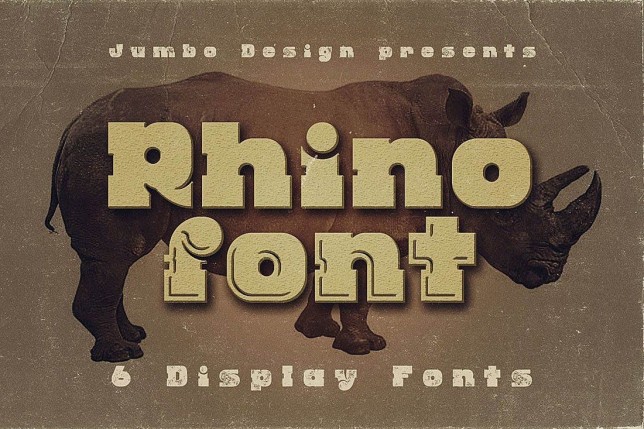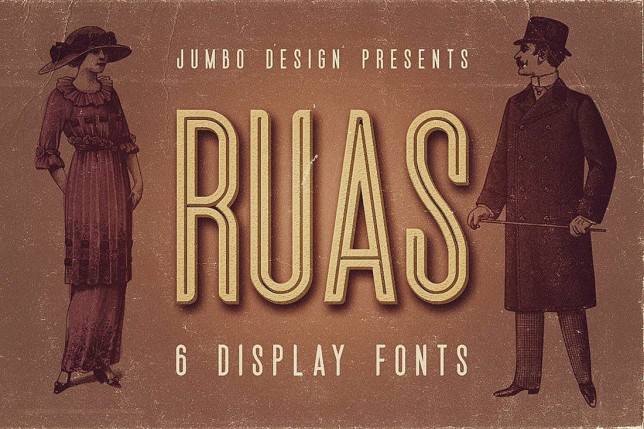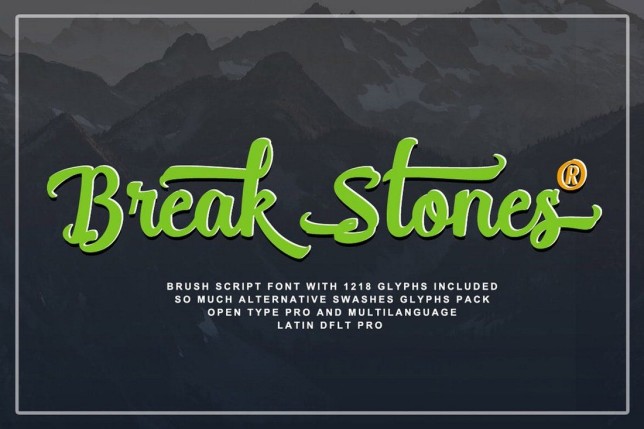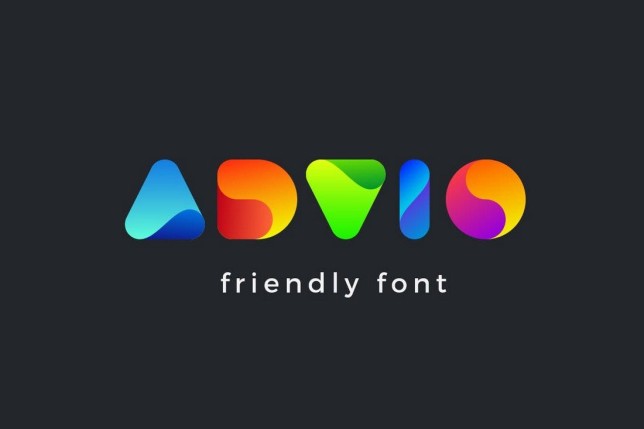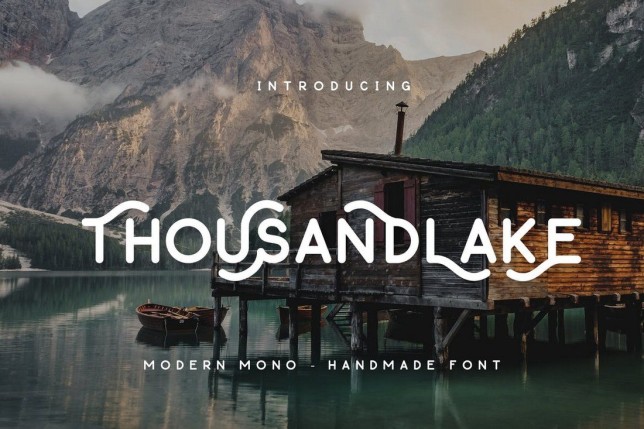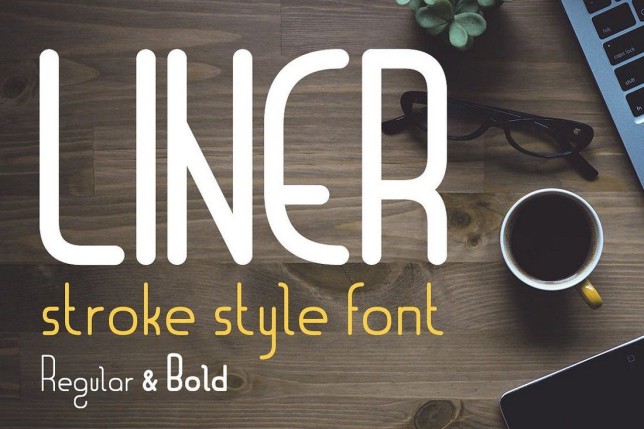
Việc thiết kế nên một logo hoàn hảo thường đòi hỏi nhiều thời gian và công sức. Bạn phải đưa ra một phác thảo thiết kế, chọn những màu sắc phù hợp, và tìm một kiểu chữ hoàn hảo để phù hợp với thương hiệu. Nhưng đừng lo, chúng tôi viết bài viết này chính là để quá trình này trở nên dễ dàng hơn cho bạn.
Không cần thiết phải dành nhiều giờ để lướt web để tìm ra một kiểu chữ tuyệt vời cho thiết kế logo của bạn, chúng tôi đã chọn ra ở đây những font chữ tốt nhất cho bạn. Hãy xem qua bộ sưu tập những kiểu chữ logo bỏ túi này của chúng tôi và chọn ra kiểu chữ phù hợp nhất cho dự án thiết kế của bạn!
Nixmat – Font chữ nhận dạng thương hiệu
Nixmat là một font chữ mang tới một thiết kế hoàn toàn khác biệt khiến nó trở nên hoàn hảo khi tạo ra bộ nhận diện thương hiệu cho doanh nghiệp của bạn. Font chữ này có thể sử dụng để thiết kế logo, hồ sơ xin việc, danh thiếp và nhiều đối tượng hơn nữa.
Bowlist – Font chữ cho logo
Bowlist là một kiểu chữ sáng tạo và đậm nét cho phép bạn có được những thiết kế logo hiện đại và phá cách. Font chữ này có thể được sử dụng cho thiết kế poster, tiêu đề website hoặc thiết kế áo phông. Nó đi kèm với bộ 376 glyph và 161 kí tự đặc biệt khác.
Oxigen – Font chữ logo tối giản
Oxigen là một font chữ logo độc đáo theo phong cách tối giản phù hợp nhất cho thiết kế logo của những thương hiệu thời trang hoặc những mặt hàng cao cấp. Nó mang lại một thiết kế đầy phong cách cũng có thể giúp bạn thiết kế nhận diện thương hiệu có thể nổi bật trước đám đông.
Raisa Script – Font chữ cho logo
Font chữ tinh tế này đi kèm với đường nét uyển chuyển một cách tự nhiên khiến nó thực sự đại diện cho sự tao nhã và thanh lịch. Kiểu chữ này lý tưởng cho việc thiết kế logo cho nhiều ngành nghề kinh doanh khác nhau cũng như tạo nên những danh thiếp, thiết kế áo phong và thiệp mời đám cưới.
Magehand – Font chữ cho logo
Magehand là một font chữ logo có một thiết kế khá sáng tạo. Nó cung cấp cả tùy chọn chữ in hoa và chữ thường cũng như nhiều kí tự thay thế đa dạng cho những ngôn ngữ khác nhau.
CAOS – Font chữ cho logo
Caos không chỉ có một thiết kế dạng monogram độc đáo thu hút sự chú ý mà còn có thể biến thiết kế của bạn thành một tác phẩm nghệ thuật. Kiểu chữ này là hoàn hảo cho việc thiết kế logo cho những hãng chuyên về sáng tạo.
Metropolia – Futuristic Font
Metropolia là một font theo phong cách Futuristic mang trong mình một thiết kế đầy sáng tạo và độc đáo. Nó phù hợp nhất khi sử dụng để thiết kế logo, danh thiếp, đầu đề trang web cho những dự án khởi nghiệp công nghệ cao và những hãng thiết kế web.
Duffish – Font chữ cho logo
Duffish là một font chữ sáng tạo cho thiết kế logo với những đường nét đậm nét và cá tính. Kiểu chữ này cung cấp đầy đủ tùy chọn với đa dạng các kí tự thay thế với những cách bố trí độc đáo giúp bạn thiết kế ra được những logo, đầu đề website hấp dẫn và nhiều hơn thế nữa.
Ornacle – Futuristic Font
Ornacle là một font chữ logo khác với phong cách Futuristic. Nó mang trong mình những đường nét sáng tạo khiến kiểu chữ này trông giống một tác phẩm nghệ thuật chạm khắc cổ xưa. Bạn có thể sử dụng nó để tạo nên những logo, poster, tiêu đề website và nhiều hơn thế nữa.
Lineat III – Font chữ sáng tạo
Họ font Lineat có đặc trưng là sự hòa trộn giữa những nét hiện đại và tương tai. Thiết kế trôi chảy dạng đường một cách sáng tạo của nó khiến kiểu chữ này lý tưởng cho việc thiết kế những logo cho những doanh nghiệp hay startup hiện đại, những nhãn hàng thời trang và thậm chí là cho cả những blogger.
RADON Monogram – Font chữ cho logo
Radon là một kiểu chữ dạng monogram với thiết kế sáng tạo mang đến một vẻ ngoài độ nhất, điều này khiến nó lý tưởng cho việc xây dựng những logo và tiêu đề trong website, danh thiếp và những thiết kế bản in. Font chữ này cũng tích hợp cả bộ chữ thường, đậm và bộ kí tự trang trí.
RibOne – Font chữ cho logo
Font chữ đầy phong cách và độc đáo này có một thiết kế đẹp mắt – khiến nó trở nên tuyệt vời cho việc thiết kế logo cho những hãng thiết kế hoặc thậm chí là tên của một sản phẩm. Nó cũng bao gồm một phiên bản web và một phiên bản chuyển sắc EPS.
Adrift Font
Nếu bạn đang thực hiện một thiết kế logo cho một thương hiệu theo chủ nghĩa tối giản hoặc thiết kế nhãn mác cho một sản phẩm, Adrift sẽ là sự lựa chọn đáng cân nhắc. Nó có 4 tùy chọn phong cách khác nhau: viết thường, trung bình, đậm và làm nhám. Font chữ dưới dạng viết tay này chắc chắn sẽ bổ sung nhiều giá trị cho những thiết kế của bạn.
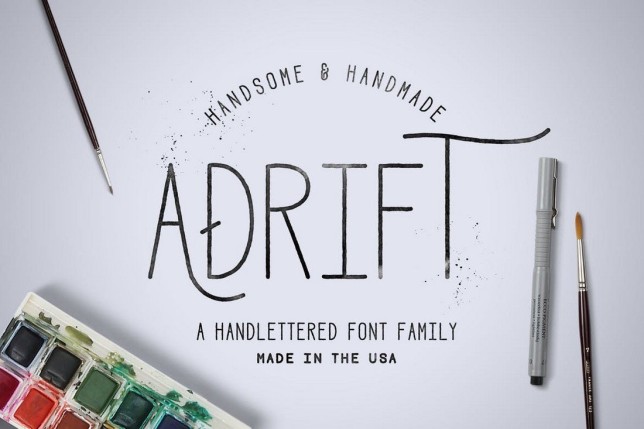
Những font chữ hoài cổ hiện đại
Những thiết kế hoài cổ hiện đại quả thực là một cơn sốt trong những năm gần đây. Font chữ này được thiết kế để giúp bạn xây dựng một logo cho thương hiệu theo sát xu hướng này. Kiểu chữ có sẵn ở 3 phong cách với những đường nét mềm mại, những đường nét tròn và một phong cách còn lại với phong cách thiết kế hỗn hợp.
Casses Font
Casses là một kiểu chữ hoàn hảo để xây dựng một logo hoặc nhãn mác sản phẩm cho quần áo hay những thương hiệu liên quan tới thời trang. Kiểu chữ này mang lại một thiết kế thủ công một cách tinh tế chắc chắn sẽ thu hút nhiều sự chú ý hơn cho thiết kế của bạn.
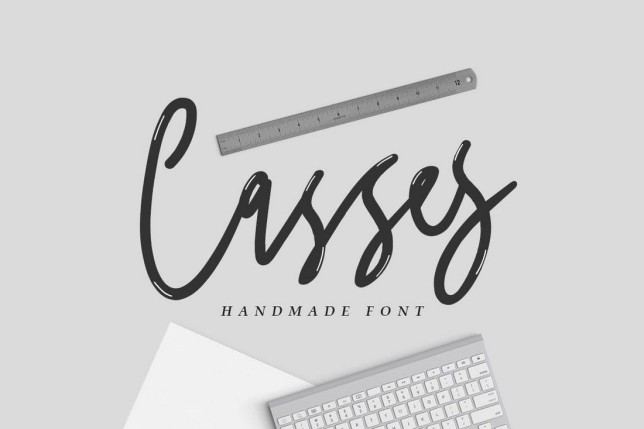
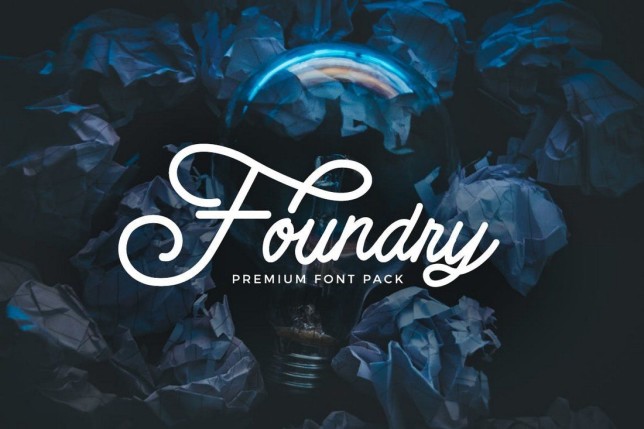
Stingo Digital Font
Lại là một font chữ mang phong cách hoài niệm-tương lai mà bạn có thể sử dụng để thiết kế logo cho những thương hiệu liên quan tới công nghệ hoặc video game. Kiểu chữ này cũng phù hợp cho việc thiết kế poster, bảng hiệu, tiêu đề website hay blog.